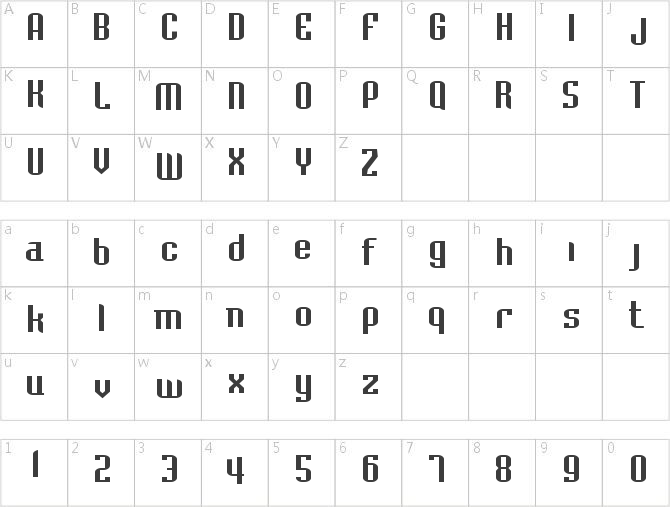
字体名称: baccuse
baccusexpandedregular
baccusexpandedregular介绍
baccusexpandedregular字体字库是一款让人赏心悦目、百看不厌的英文字体,适合各类广告和产品包装设计应用,字体大小0.04MB,格式为ttf字体,上传用户是Apple,作者/版权方为未知